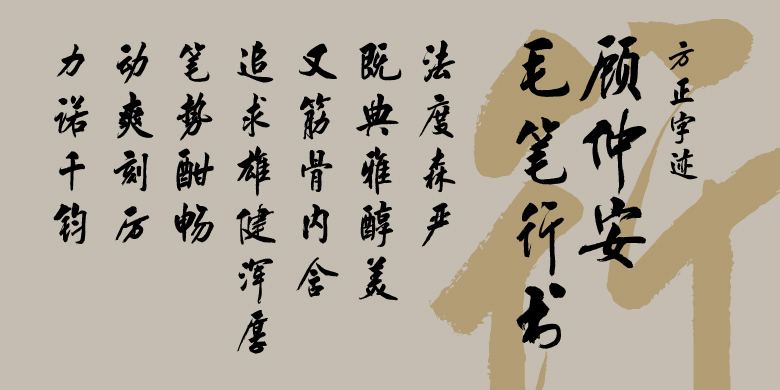
方正字迹-顾仲安毛笔行书
方正字迹-顾仲安毛笔行书,这款字体结构工整、笔画清晰,兼顾美观与易读性,适用于标题、正文、海报、包装、LOGO 等多种场景。字形优雅稳定,风格百搭耐看,适配日常排版与创意设计,让文字呈现更舒适、更具质感。方正字迹-顾仲安毛笔行书一笔一画,皆是细节,以均衡的比例、流畅的线条打造舒适视觉体验,字形端正大气,风格简约现代。无论是商业设计、品牌宣传还是日常排版,都能轻松驾驭,让文字更有格调与力量。方正字迹-顾仲安毛笔行书字体下载。
作者书写顾仲安毛笔行书字库,继承了传统书法风格,又结合自己习字、创作心得,无论是字形结构还是线条变化都表现出厚重凝练,法度森严。既典雅醇美,又筋骨内含。
追求雄健浑厚,笔势酣畅,动爽刻厉、力诺千钧,同时又不失神采飘逸,灵动洒脱。大气豪迈,清健雅致,结体道劲,劲气沛然,字字严谨入古味。
这种风格的字体主要体现高端大气,风流蕴藉,摇曳生姿,似行云流水,清新脱俗,刚柔并济,一气呵成。让人赏心悦目,常看常新,有酣畅淋漓,神清气爽,心旷神怡的感觉,并集作者一个多甲子的功力,笔老墨秀,形成了顾体行书固有的特质。